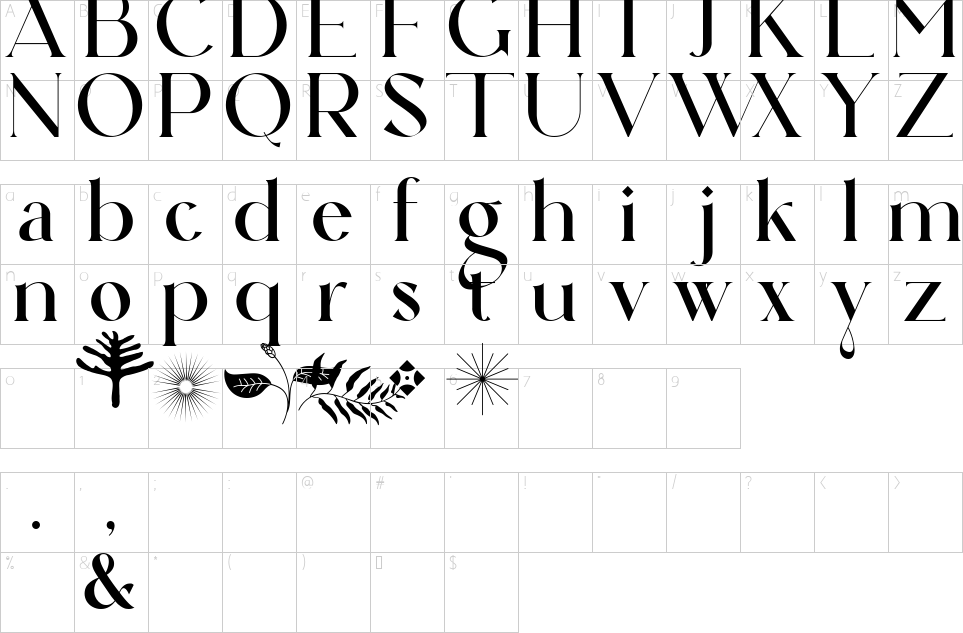
Ahganirya Font
A Ahganirya Font é uma elegante e sofisticada escolha para aqueles que valorizam um estilo moderno e minimalista na composição de textos. Desenvolvida por Putu Dody Permana, essa fonte oferece uma ampla gama de opções para personalizar seu design. A Ahganirya é perfeita para aqueles que buscam uma fonte fácil de ler e que combina perfeitamente com diversas aplicações, desde sites e blogs até projetos de design gráfico profissional. Seu design minimalista e moderno fazê-la se destacar em qualquer projeto. Apesar de ser uma fonte de código aberto, ela se apresenta de maneira profissional, garantindo um resultado impecável em qualquer dispositivo. Com a Ahganirya Font, você está garantindo um toque de criatividade e sofisticação em qualquer projeto que escolher. Descubra por si mesmo o poder da Ahganirya Font e deixe sua marca com estilo.
Mapa de caracteres da fonte Ahganirya Font